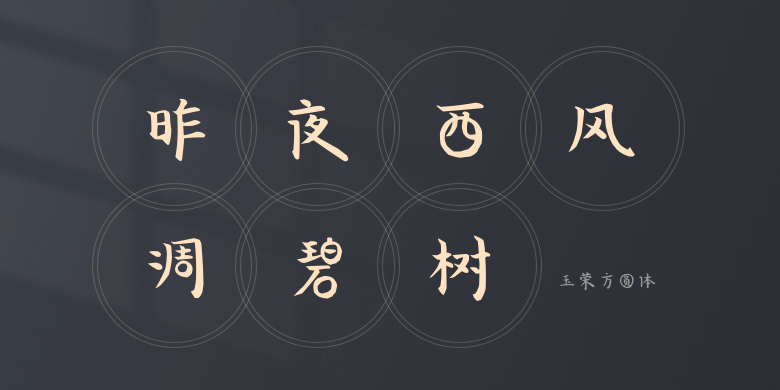
玉荣方圆体
玉荣方圆体,这款字体结构工整、笔画清晰,兼顾美观与易读性,适用于标题、正文、海报、包装、LOGO 等多种场景。字形优雅稳定,风格百搭耐看,适配日常排版与创意设计,让文字呈现更舒适、更具质感。玉荣方圆体一笔一画,皆是细节,以均衡的比例、流畅的线条打造舒适视觉体验,字形端正大气,风格简约现代。无论是商业设计、品牌宣传还是日常排版,都能轻松驾驭,让文字更有格调与力量。玉荣方圆体字体下载。